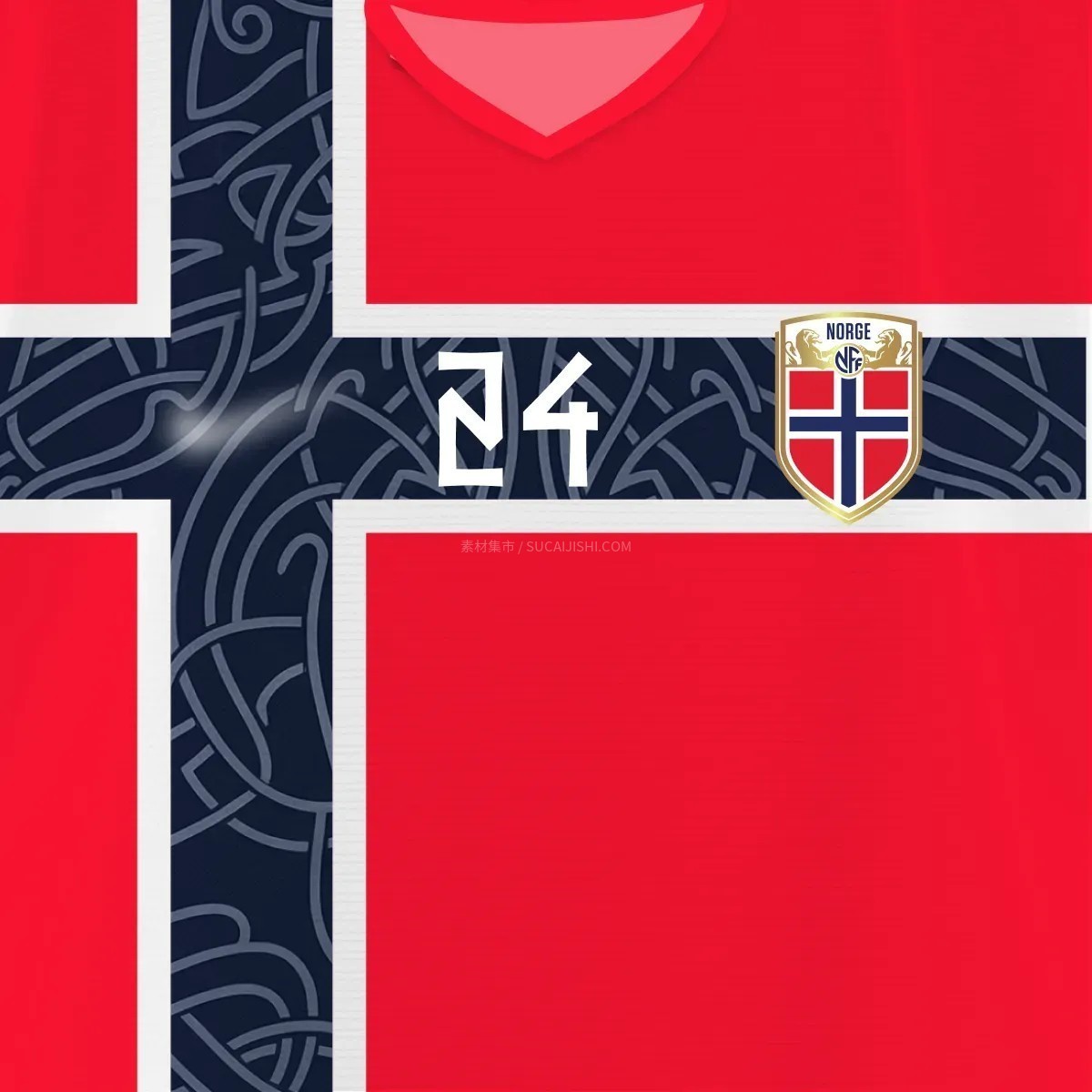
挪威2026世界杯球衣字体
挪威队2026年FIFA世界杯球衣上的视觉字体。设计深植于传统维京卢恩字母,线条棱角分明,几何结构流畅,呈现出仿佛从石头上凿刻而成的原始硬核质感。极致的黑白对比设计带来了强烈的视觉冲击力。每个字符的比例、粗细和间距均经过逐字精调与对比研究,完美再现赛场上深沉且极具力量感的北欧风情。